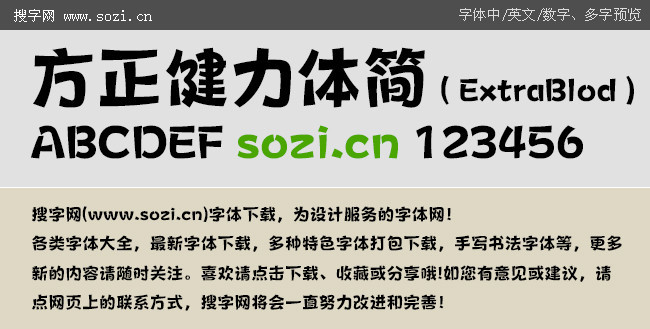
方正健力體簡ExtraBlod
搜字網(wǎng)提供一款方正健力體簡中文字體下載,方正健力體是作者從某健身的標志引發(fā)的靈感,點,撇,捺,抅,橫,直劃等都是不同方向,也好像各種健身項目的不同表達方式一樣,是一款充滿動感和活力的字體。適合健美行業(yè),活力飲料,運動服裝和運動鞋的廣告宣傳。